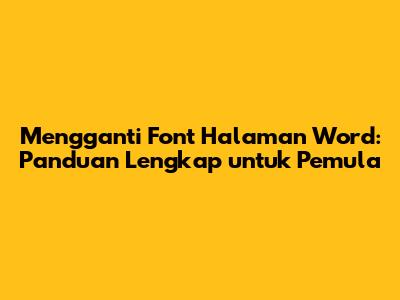
- Buka Dokumen Word Anda: Buka dokumen Word yang ingin Anda ubah font-nya. Jika Anda belum memiliki dokumen, buat dokumen baru terlebih dahulu.
- Pilih Teks yang Ingin Diubah: Sorot teks yang ingin Anda ubah font-nya. Anda dapat memilih seluruh dokumen dengan menekan Ctrl + A (Windows) atau Command + A (Mac). Jika Anda hanya ingin mengubah font untuk bagian tertentu, cukup sorot teks tersebut dengan kursor.
- Buka Menu Font: Ada dua cara utama untuk mengakses menu font:
- Ribbon: Di tab "Beranda" (Home), Anda akan melihat bagian "Font". Di sini, Anda dapat melihat font saat ini, ukuran font, dan opsi lain terkait font.
- Kotak Dialog Font: Klik ikon kecil di sudut kanan bawah bagian "Font" pada ribbon. Ini akan membuka kotak dialog Font, yang menawarkan lebih banyak opsi, seperti gaya font (tebal, miring, dll.), efek (coretan, subskrip, dll.), dan pengaturan lanjutan.
- Pilih Font yang Diinginkan: Di menu Font atau kotak dialog Font, klik menu drop-down yang menampilkan nama font saat ini. Daftar semua font yang tersedia di komputer Anda akan muncul. Gulir ke bawah dan pilih font yang Anda inginkan. Anda dapat melihat pratinjau font saat Anda mengarahkannya.
- Sesuaikan Ukuran dan Gaya Font: Setelah memilih font, Anda dapat menyesuaikan ukuran dan gaya font. Gunakan menu drop-down ukuran font untuk memilih ukuran yang sesuai. Gunakan tombol B (tebal), I (miring), dan U (bergaris bawah) untuk menyesuaikan gaya font.
- Terapkan Perubahan: Setelah Anda selesai menyesuaikan font, klik "OK" untuk menerapkan perubahan pada teks yang dipilih. Jika Anda ingin mengubah font untuk seluruh dokumen, pastikan Anda telah memilih seluruh dokumen sebelum mengikuti langkah-langkah di atas.
- Gunakan Judul dan Subjudul: Gunakan judul dan subjudul yang berbeda dari teks utama untuk membantu pembaca memahami struktur dokumen Anda. Gunakan font yang lebih besar dan gaya yang berbeda (misalnya, tebal) untuk judul dan subjudul.
- Perhatikan Spasi: Pastikan ada cukup spasi antara paragraf dan antara baris teks. Hal ini akan membuat dokumen Anda lebih mudah dibaca. Gunakan fitur "Paragraf" di Word untuk menyesuaikan spasi.
- Gunakan Font yang Mudah Dibaca: Pilih font yang mudah dibaca, terutama untuk teks utama. Hindari font yang terlalu dekoratif atau rumit.
- Gunakan Konsistensi: Gunakan font yang sama di seluruh dokumen Anda untuk menjaga konsistensi dan tampilan yang rapi.
- Hindari Terlalu Banyak Font: Jangan menggunakan terlalu banyak font yang berbeda dalam satu dokumen. Hal ini dapat membuat dokumen terlihat berantakan. Gunakan maksimal dua atau tiga font yang berbeda.
- Gunakan Warna Font yang Tepat: Pilih warna font yang sesuai dengan latar belakang dokumen Anda. Pastikan warna font mudah dibaca dan tidak terlalu mencolok.
- Gunakan Fitur Format Painter: Jika Anda ingin menerapkan format font yang sama ke bagian lain dari dokumen Anda, gunakan fitur "Format Painter". Fitur ini memungkinkan Anda untuk menyalin format font dari satu bagian teks ke bagian lain.
- Simpan Pengaturan Font sebagai Gaya: Jika Anda sering menggunakan format font tertentu, simpan pengaturan font tersebut sebagai gaya. Ini akan memudahkan Anda untuk menerapkan format yang sama ke dokumen lain.
- Laporan Bisnis: Untuk laporan bisnis, pilihlah font yang profesional dan mudah dibaca, seperti Arial, Calibri, atau Times New Roman. Gunakan ukuran font yang lebih besar (misalnya, 12 poin) untuk memudahkan pembacaan.
- Surat Lamaran Kerja: Untuk surat lamaran kerja, pilihlah font yang profesional dan bersih, seperti Arial, Calibri, atau Helvetica. Hindari font yang terlalu dekoratif atau kasual.
- Presentasi: Untuk presentasi, pilihlah font yang mudah dibaca dari kejauhan, seperti Arial, Arial Black, atau Impact. Gunakan ukuran font yang lebih besar dan gaya yang lebih berani.
- Dokumen Akademik: Untuk dokumen akademik, pilihlah font yang formal dan mudah dibaca, seperti Times New Roman atau Garamond. Ikuti pedoman gaya yang diberikan oleh institusi Anda.
- Dokumen Kreatif: Untuk dokumen kreatif, Anda dapat lebih bebas dalam memilih font. Namun, pastikan font yang Anda pilih sesuai dengan tema dokumen Anda dan mudah dibaca.
Mengganti font halaman Word adalah keterampilan dasar yang perlu dikuasai bagi siapa saja yang sering berurusan dengan dokumen. Baik itu tugas sekolah, laporan pekerjaan, atau sekadar menulis surat, pemilihan font yang tepat dapat membuat perbedaan besar dalam tampilan dan keterbacaan dokumen Anda. Guys, jangan khawatir jika kalian baru pertama kali mencoba, karena prosesnya sangat mudah diikuti. Dalam panduan ini, kita akan membahas secara detail cara mengganti font halaman Word, mulai dari langkah-langkah dasar hingga tips untuk memilih font yang paling sesuai.
Memahami Pentingnya Pemilihan Font yang Tepat
Sebelum kita mulai membahas cara mengganti font halaman Word, ada baiknya kita memahami mengapa pemilihan font begitu penting. Font bukan hanya sekadar kumpulan huruf dan simbol, melainkan juga elemen visual yang dapat memengaruhi cara orang lain memandang dokumen Anda. Font yang tepat dapat membuat dokumen terlihat lebih profesional, mudah dibaca, dan menarik perhatian. Sebaliknya, font yang salah dapat membuat dokumen terlihat berantakan, sulit dibaca, dan bahkan memberikan kesan yang kurang profesional. Pikirkan tentang font sebagai pakaian untuk dokumen Anda. Pakaian yang tepat akan membuat Anda terlihat lebih baik, bukan? Begitu pula dengan font. Font yang tepat akan membuat dokumen Anda terlihat lebih baik dan mudah dipahami.